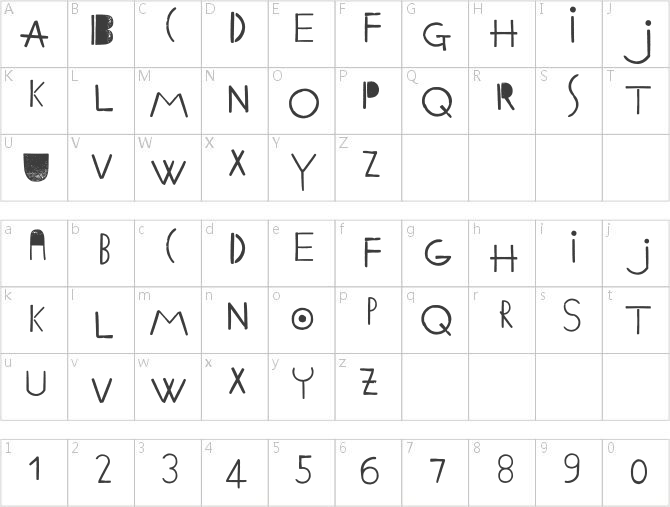
字體名稱: ethnica
ethnicabc-regular-webfont介紹
ethnicabc-regular-webfont字體字庫是一款讓人賞心悅目、百看不厭的英文字體,適合各類廣告和產品包裝設計應用,字體大小0.25MB,格式為ttf字體,上傳用戶是shiqiuping,作者/版權方為未知